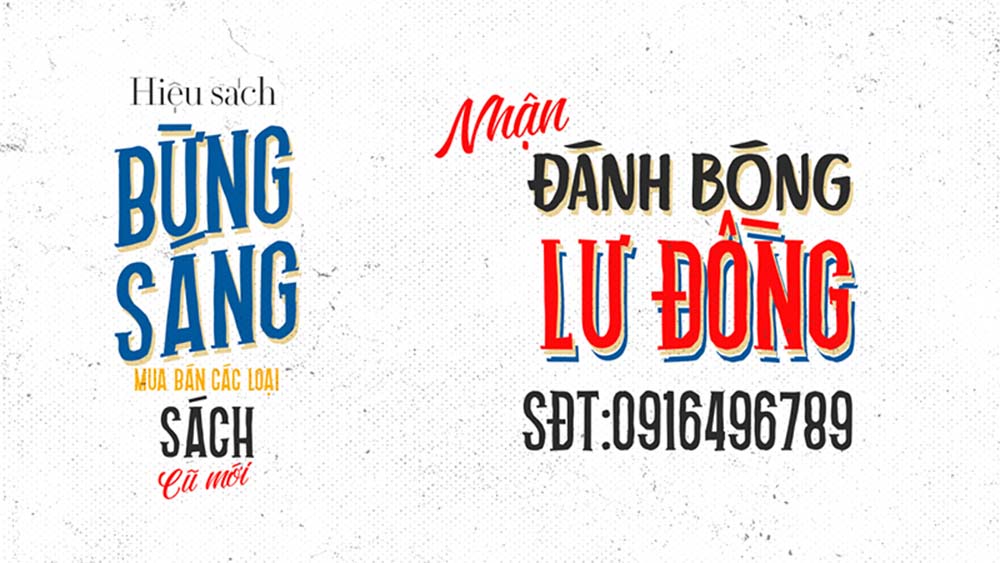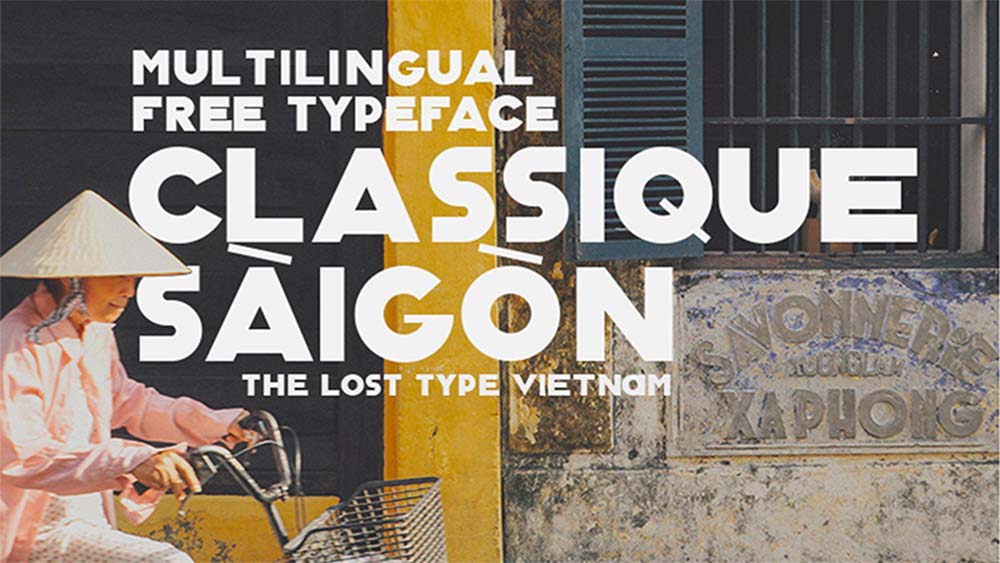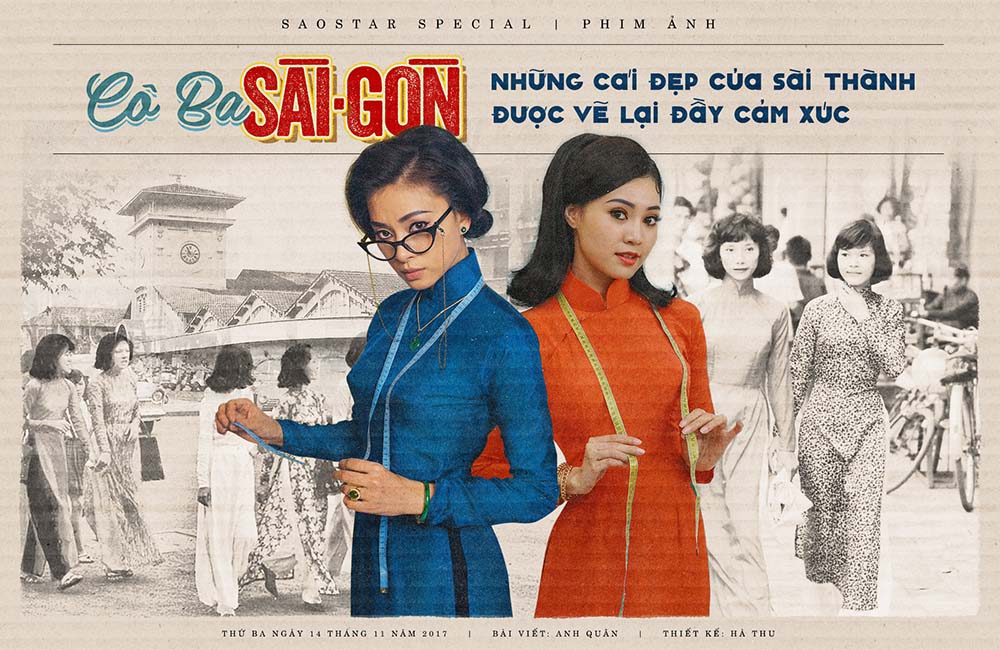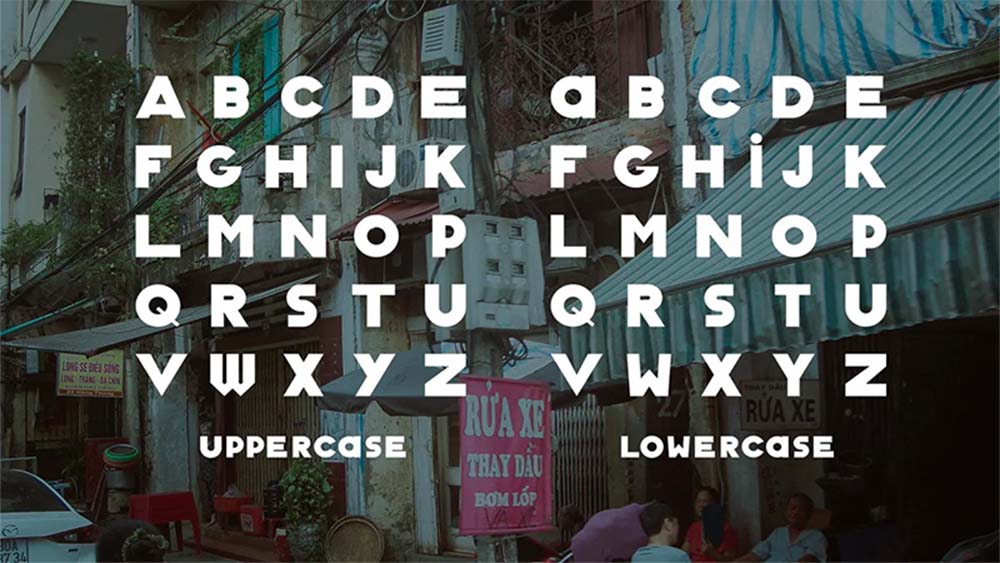
Tổng Hợp 70 Font Chữ Việt Hóa Thời Bao Cấp Hoài Cổ Miễn Phí
Phong cách vintage và retro vẫn chưa bao giờ lỗi thời so với cái ý nghĩa cổ điển của nó, trong lĩnh thiết kế thời trang cũng như trong thiết kế đồ họa, hơi hướng cổ điển vẫn có thể tạo nên cho bạn 1 tác phẩm thật hoàn hảo mang vẻ đẹp cổ điển và có nét gì đó hiện đại.
Các bạn có thể xem những tấm hình demo cho bộ 70 font mà D3design sắp chia sẻ, bằng việc kết hợp với các texture giấy cũ và brush, dường như nó làm tôn vinh lên vẻ đẹp rất cổ điển của bộ font này, bạn có thể tạo nên 1 poster mang phong cách cổ điển như thế này.
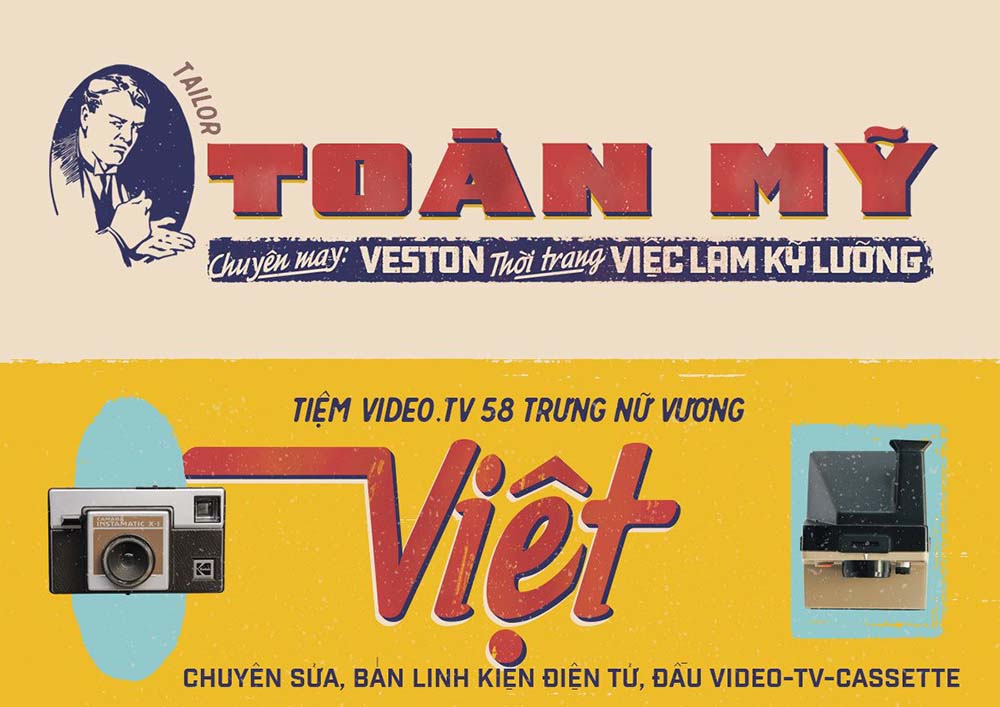
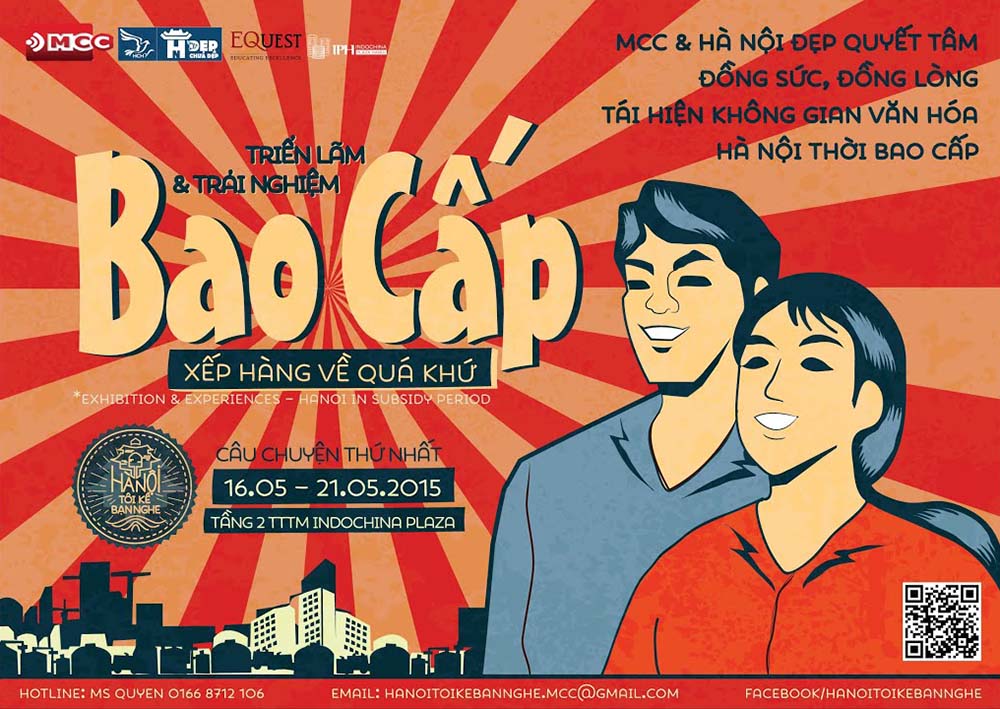
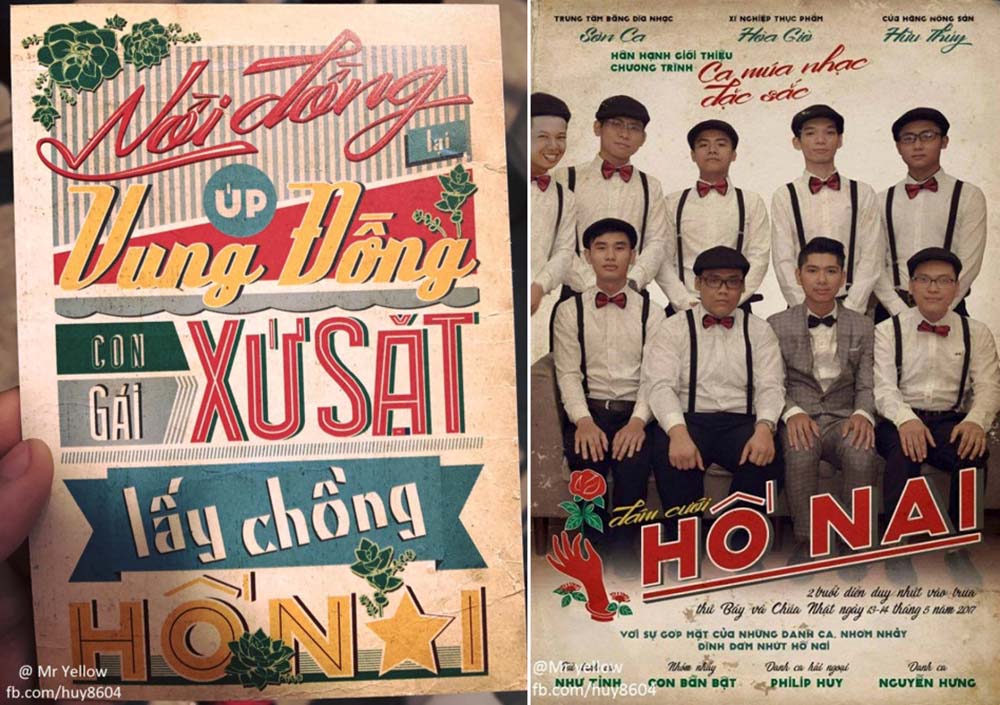
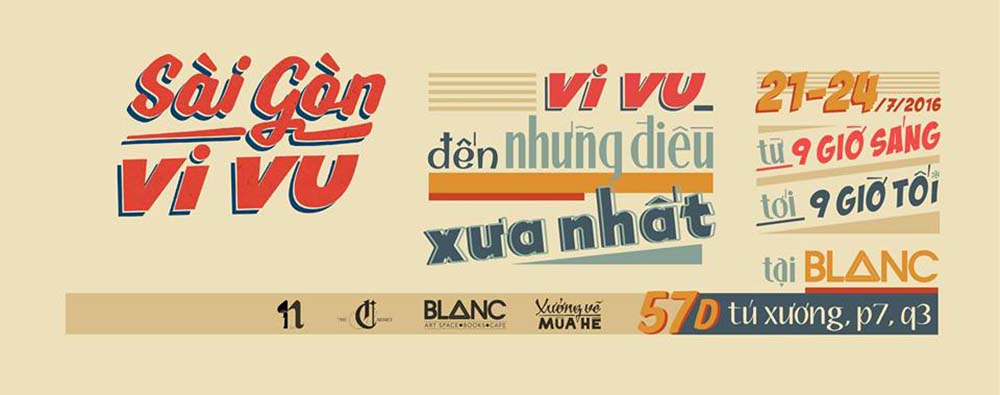
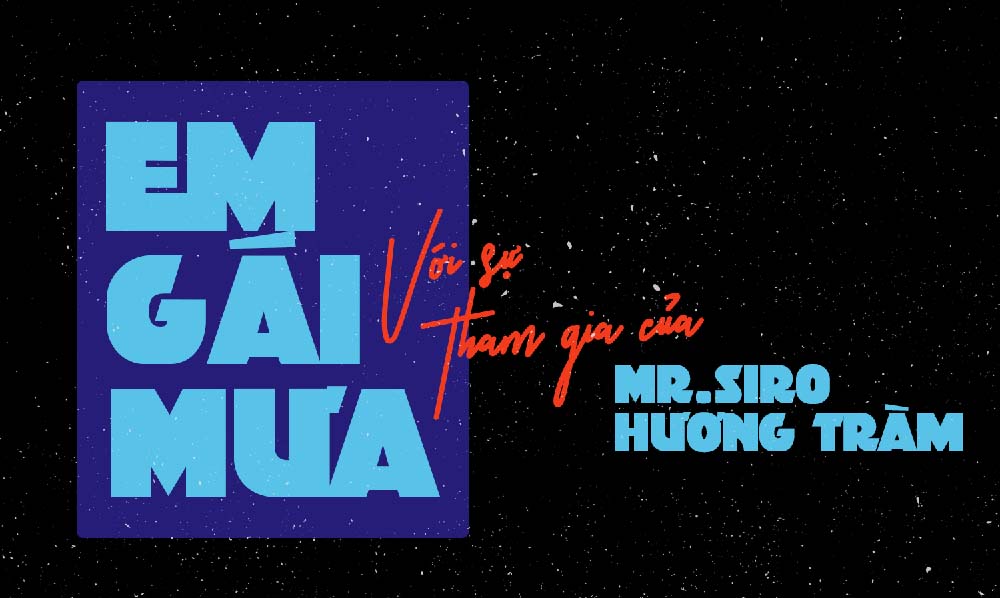
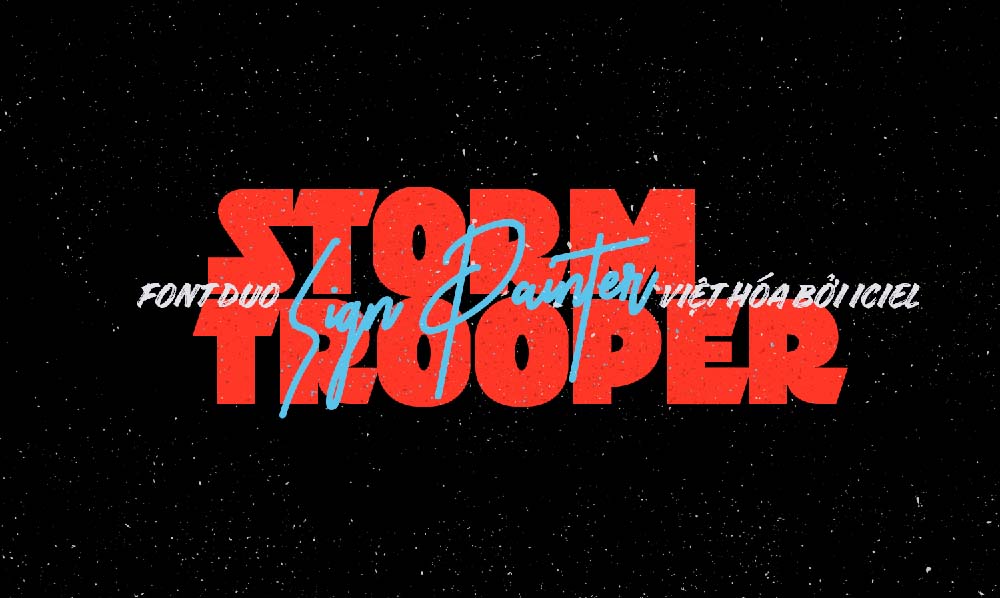
Hi vọng bài tổng hợp font chữ thời bao cấp và các font retro trên đây sẽ giúp bạn có thêm nhiều lựa chọn về typography cho các thiết kế hoài cổ của mình nhé.